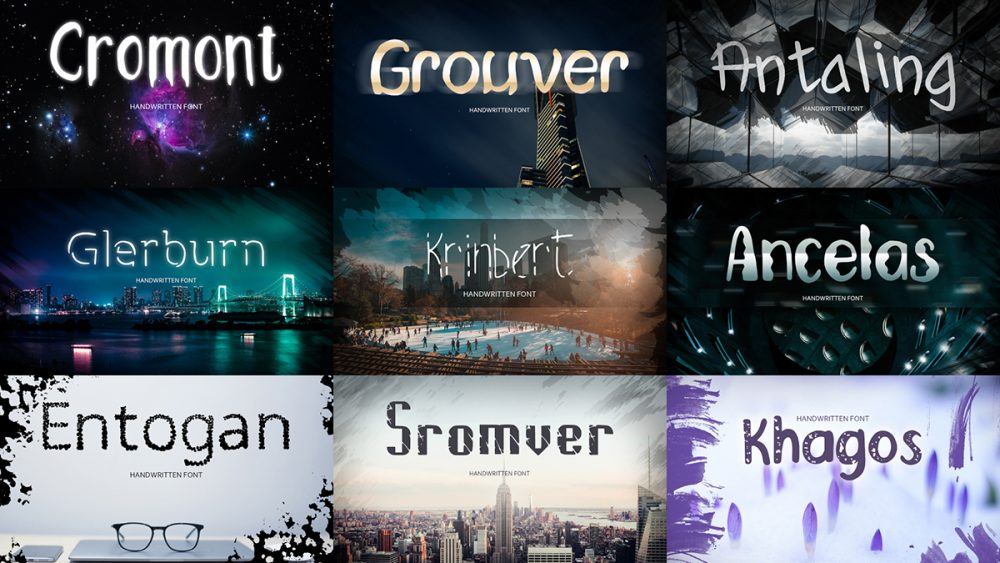
Bu harika yazı tipi paketi benzersiz, ayrıntılı ve el yapımı bir görünüme sahiptir. İster büyük harflerle şık bir görünüm, ister küçük harflerle güzel bir görünüm denemek isteyin, bu yazı tipi paketi tamamen zamansız bir şey için tasarlanmıştır.
Muhteşem logolar, görüntüler, başlıklar, davetiyeler, tarihleri kaydetme, düğünler, başlıklar, web düzenleri ve markalama vb. için mükemmeldir.
250 Profesyonel yazı tipinden oluşan muhteşem bir koleksiyon
Çeşitli alternatif karakterleri karıştırıp eşleştirebileceğiniz inanılmaz derecede esnek set.